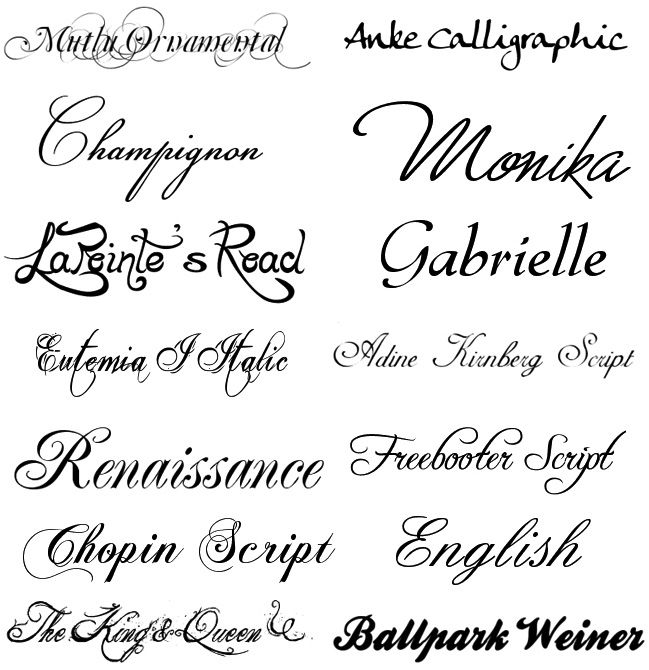
Красивый текст шрифт: Красивые шрифты онлайн | Написать текст и скопировать
Красивый шрифт для текста онлайн на русском, каталог для Инстаграма, скопировать для ника
Aesthetic
Эстетика
ꍏꈤꉓꀤꍟꈤ꓄
Древний
🅱🅻🅰🅲🅺 🆂🆀🆄🅰🆁🅴
Чёрный квадрат
🅑🅛🅐🅒🅚 🅑🅤🅑🅑🅛🅔
Чёрный круг
𝐁𝐨𝐥𝐝
Жирный
𝘽𝙤𝙡𝙙 𝙄𝙩𝙖𝙡𝙞𝙘
Жирный курсив
𝘐𝘵𝘢𝘭𝘪𝘤
Курсив
🎗〽️⚽🎷🎐
Эмодзи
𝔊𝔬𝔱𝔥𝔦𝔠
Готический
ᴦᴇᴧьʙᴇᴛиᴋᴀ
Заглавные буквы
З̶а̶ч̶ё̶р̶к̶н̶у̶т̶ы̶й̶
Зачёркнутый
U̲n̲d̲e̲r̲l̲i̲n̲e̲
Подчёркнутый
Д̳в̳о̳й̳н̳а̳я̳ ч̳е̳р̳т̳а̳
Двойное подчёркинвание
【С】【к】【о】【б】【к】【и】
Чёрные скобки
𝓑𝓸𝓵𝓭 𝓢𝓬𝓻𝓲𝓹𝓽
Рукописный жирный
ᚹᚴᚺᚤ
Руны
𝐻𝒶𝓃𝒹𝓌𝓇𝒾𝓉𝒾𝓃𝑔
Рукописный
『У』『г』『о』『л』『к』『и』
Уголки
Γρεεκ
Греческий
∩dsᴉpǝpoʍu
Перевёрнутый
🄿🄾🄻🄴 🄲🄷🅄🄳🄴🅂
Поле чудес
ጓዋሀዐከሀጸ
Эфиопия
Шрифты – это инструмент, который помогает сделать сайт или социальную сеть более запоминающейся.
С помощью красивых заголовков или надписей можно подчеркнуть значащую часть поста, оформить ник в Instagram и заинтересовать аудиторию. Статья, исполненная в необычном стиле, сразу привлекает внимание.
Чтобы выделиться среди тысяч интернет-источников, вы воспользуйтесь нашим сервисом, насчитывающим множество стилей оформления текста. Мы подобрали несколько десятков вариантов начертаний букв на любом языке. Вам не придётся скачивать специальные приложения. Изменить шрифт можно онлайн с помощью удобного интерфейса.
Как работает сервис
Для создания оригинального текста вам нужно выполнить всего 3 действия.
Сначала выберите шрифт. На странице сервиса представлен каталог с вариантами написания текста с примерами, от обычных декоративных рукописных шрифтов до эмоджи или изображений. Когда выбираете оформление, ориентируйтесь на содержание вашей статьи и общую стилистику сайта. Предложения должны не только красиво выглядеть, но и раскрывать смысл поста.![]()
После выбора подходящего эффекта вставьте надпись, которую вы хотите оформить, в специальное окно «Ваш текст». Сервис автоматически стилизует распознанные символы и выведет результат. Вам останется скопировать готовую статью и применить её в своих целях.
Генератор работает по простому механизму. Он считывает введённые буквы, вне зависимости от языка. Они могут быть написаны на русском или английском — это не играет роли. Затем сервис сопоставляет их с библиотекой символов, заложенной в выбранном шрифте, изменяя исходные данные, на данные из этой библиотеки. Вы же получаете результат в один клик.
Где использовать шрифты
Сначала может показаться, что стиль текста в статье не играет никакой роли. Однако практика говорит об обратном. Пользователи соцсетей лучше реагируют на оформленные посты, где предложения не просто правильно составлены, но и красиво написаны. Этот подход позволяет выделиться среди множества других источников информации.
Пользователь с большей вероятностью запомнит необычные начертания, чем классический Times New Roman или Calibri.
При просмотре вашей публикации в Instagram потенциальный подписчик обращает внимание на 3 пункта: картинка или фотография, содержательная часть поста, профиль автора. Все три пункта должны дополнять друг друга и выделяться среди прочего контента соцсети. Здесь красивые шрифты будут очень полезны.
Не менее важно оформлять текст при разработке своего сайта. Веб-дизайнеры точно знают, что шрифт влияет на восприятие и может подтолкнуть читателя к совершению целевого действия. С помощью эффектов часто выделяют значащую часть статьи, подчеркивают главную мысль или, наоборот, отводят внимание читателя от определённых слов.Как сделать красивый шрифт в Инстаграм: в шапке профиля, имени, нике или посте
В Инстаграм нередко попадаются аккаунты с необычными шрифтами. В имени аккаунта, описании профиля или тексте поста.
В статье расскажем, как сделать красивый шрифт в Инстаграм, где искать шрифты и как их использовать.
Как сделать красивый шрифт в Инстаграм: в шапке профиля, в имени пользователя или посте
В Инстаграм нет возможности выбрать шрифт текста или добавить свой. Все делается через сторонние приложения и сайты.
Все они работают по аналогии:
- Находим сайт или приложение со шрифтами.
- Пишем текст.
- Выбираем шрифт.
- Копируем слово или словосочетание.
- Вставляем в Инстаграм в нужное поле (например, в поле имени или описания аккаунта). Делается через редактирование профиля.
Важно: большинство сайтов и приложений работают только с латиницей. А если есть кириллица, то там меньше вариантов шрифтов.
Добавляем красивый шрифт в описание профиля Инстаграм
В качестве примера рассмотрим приложение Fontify — Fonts for Instagram, которое как раз заточено под использование в Инстаграм, но можно копировать шрифты и в другие соцсети / мессенджеры.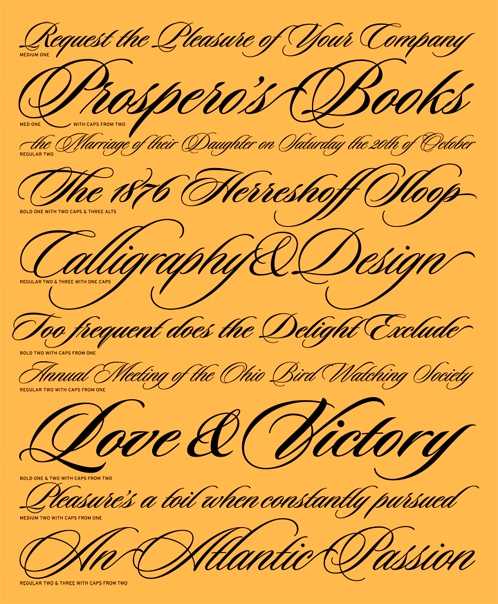
Важно: чтобы использовать этот метод для Инсты, предварительно нужно будет перенести буквы в текстовый редактор, а потом уже копировать целым словом и переносить в профиль Инстаграм.
Lingojam.com — очень простой сайт из двух окон. В левом пишем слово, в правом появляются шрифты. Доступно для выбора около 100 вариантов.
Fancytextguru.com — похож на предыдущий, но тут намного больше шрифтов.
Еще пара аналогов — Fancytextpro.com и Fancyfonts.top.
ЗаключениеДобавить необычный шрифт в Инстаграм проще, чем кажется.